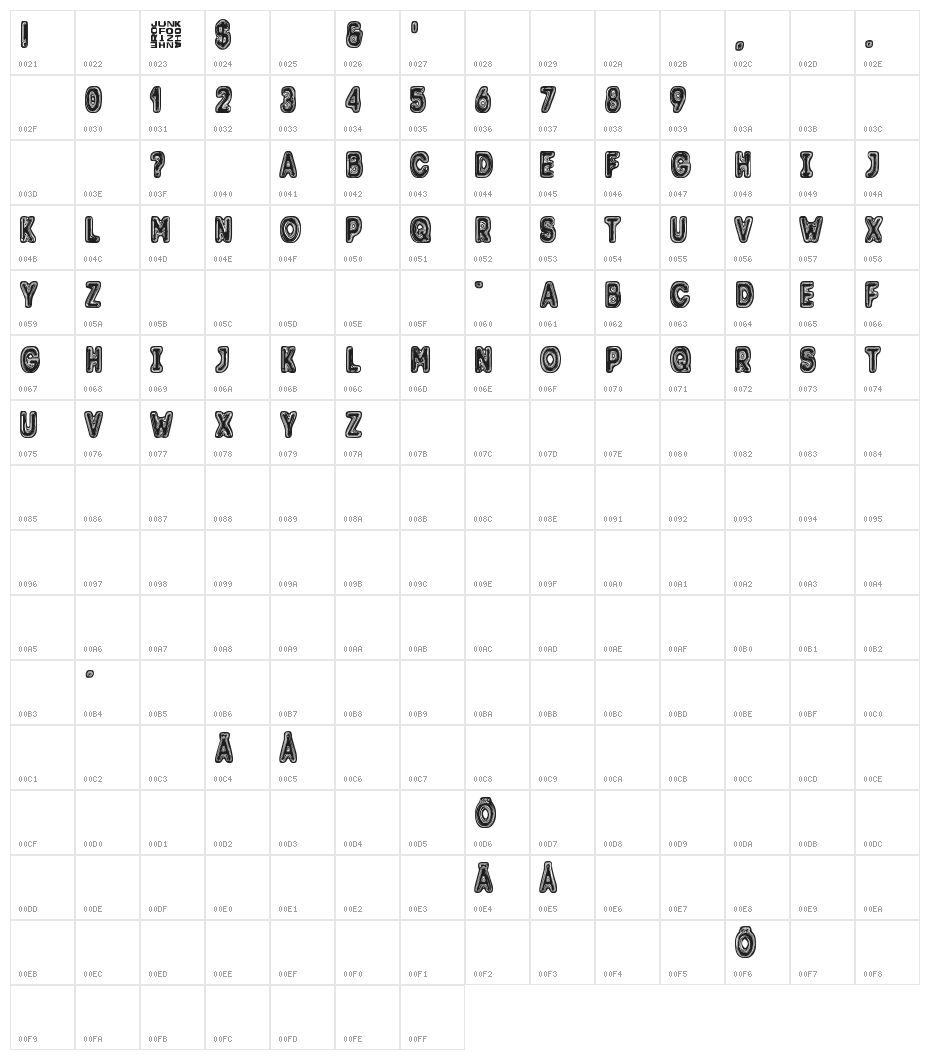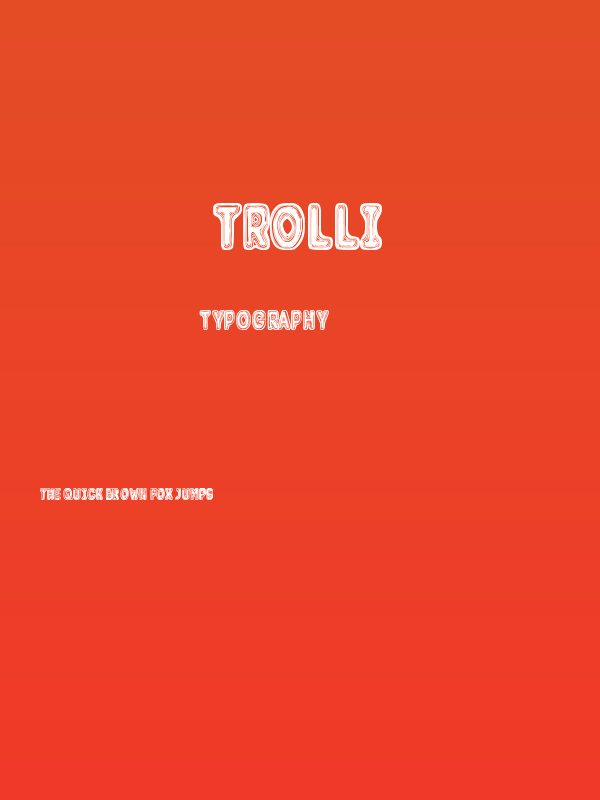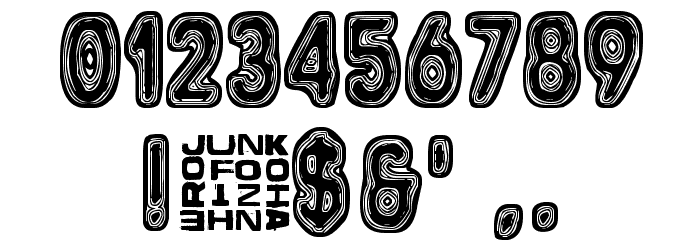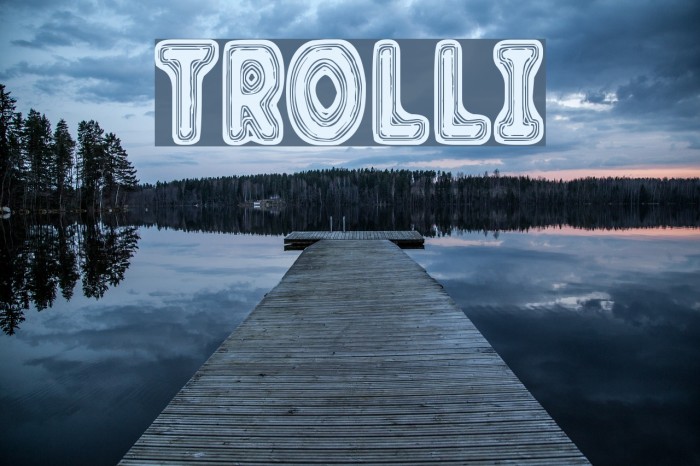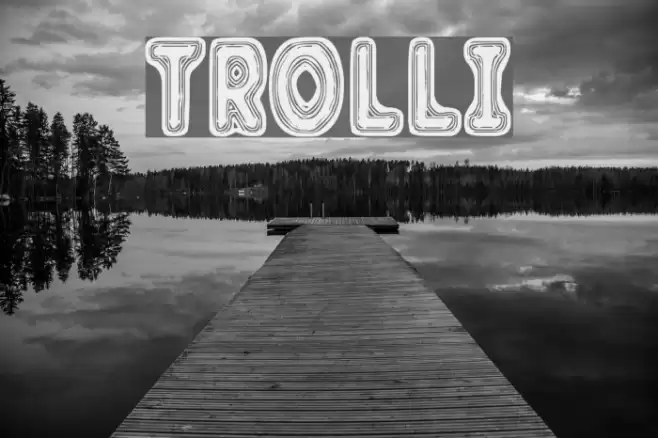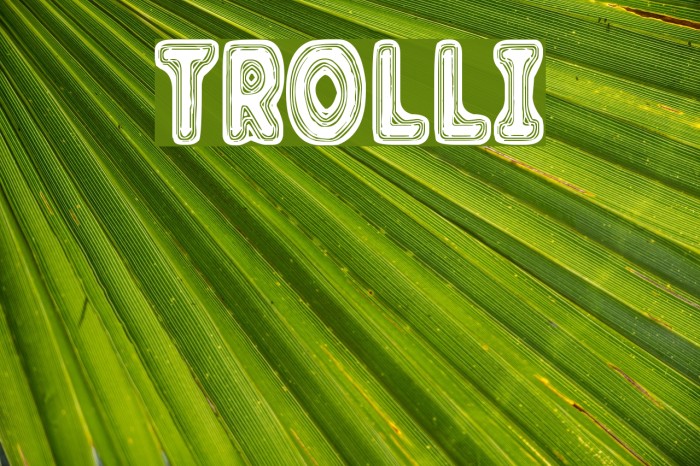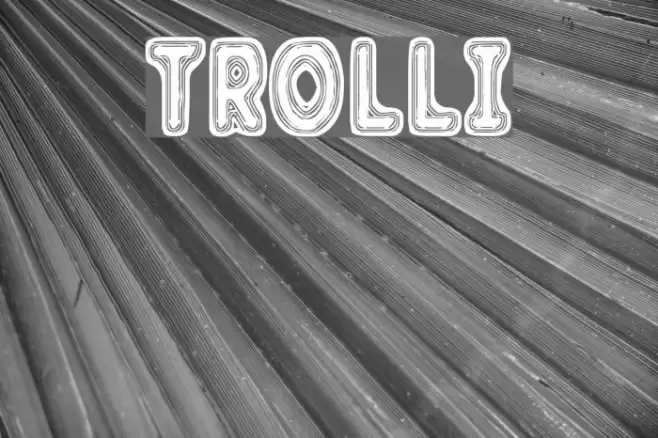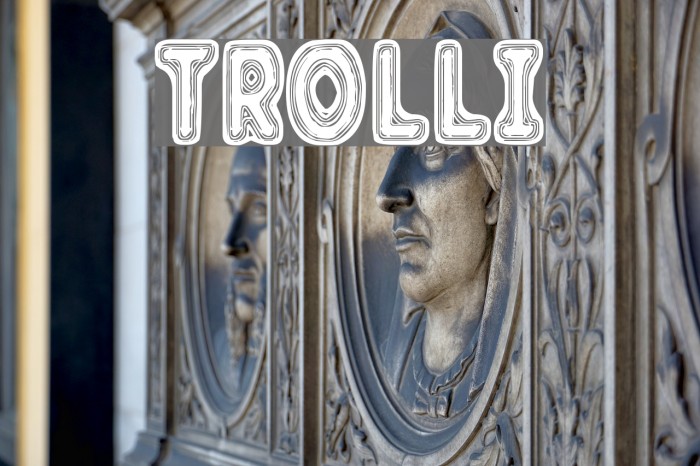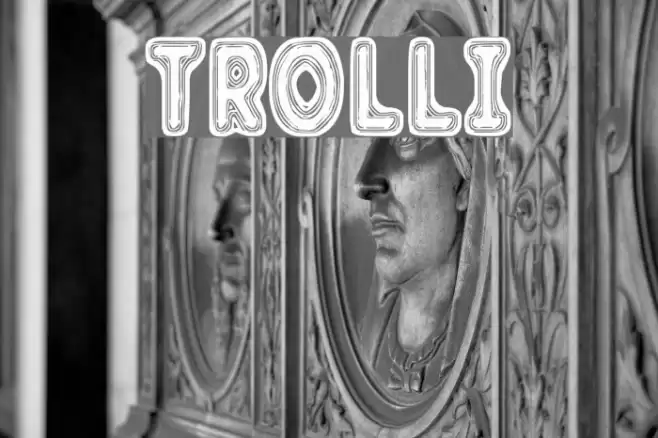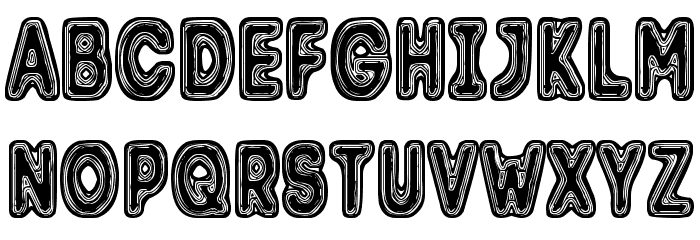
Trolli Font
✎ Distorted Eroded
| カテゴリ | Distorted Eroded |
| 全体的なスタイル | Vintage, Decorative |
| おすすめプロジェクト | Ideal for posters, children's book covers, party invitations, and branding for playful products. |